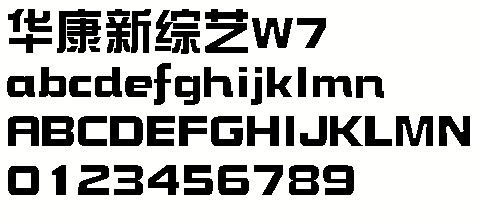
華康新綜藝體是一款極具特色的電腦字體,字體端正具有張力常用于多種行業(yè)領(lǐng)域,在本站一鍵下載安裝即可使用,深受廣大用戶喜愛??靵砭G色資源網(wǎng)下載體驗吧!
華康新綜藝W7是一套常見及常用的POP廣告字體,以黑體為基本出發(fā)點,外觀更趨方正,外張,結(jié)構(gòu)與筆劃更善于平均分布,擺脫了傳統(tǒng)黑體之規(guī)范,更具自由。適用于一般海報,報紙,雜志標題,用途廣泛,很多產(chǎn)業(yè)都可通用,如宣傳橫額,燈箱,招牌等。